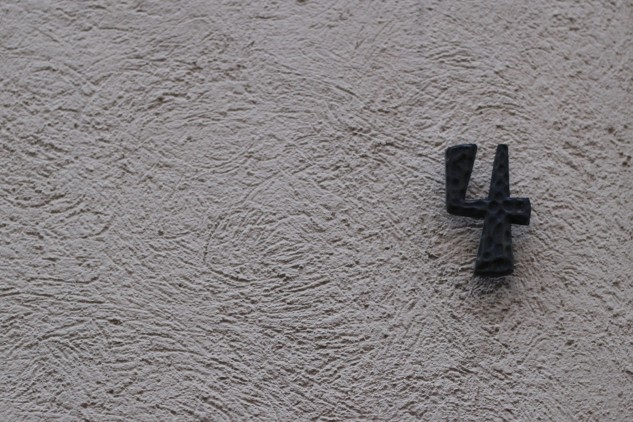
Vier an der Wand Chris Foraita, Heidelberg # 04/12/13 Categories: Freestyle Tags: Hausnummer, Kunstschlosser, Metall, Nummer, Orientierung, Wand, Ziffer Freestyle von einem Kunstschlosser 408 Likes